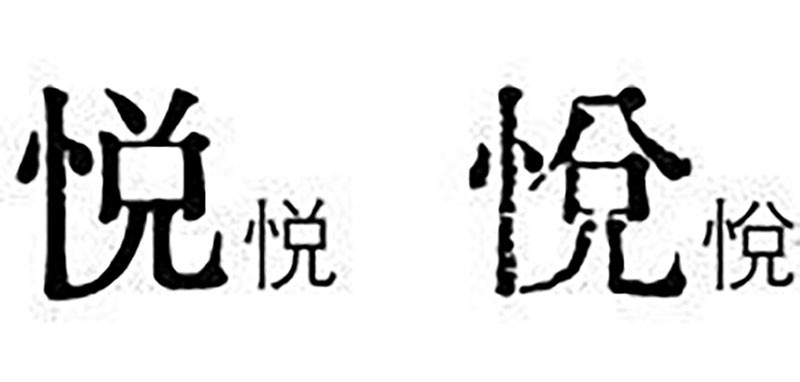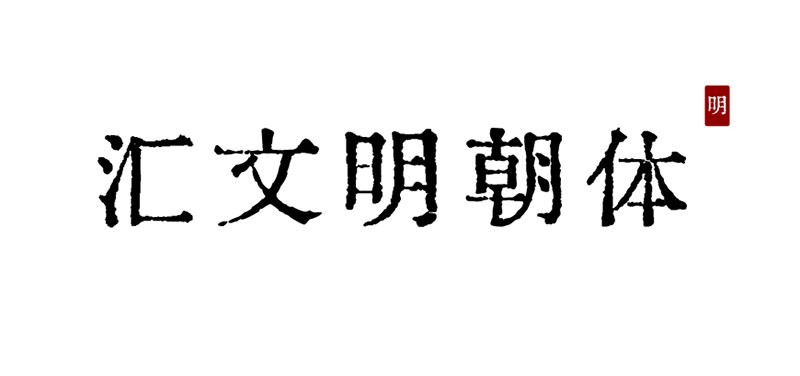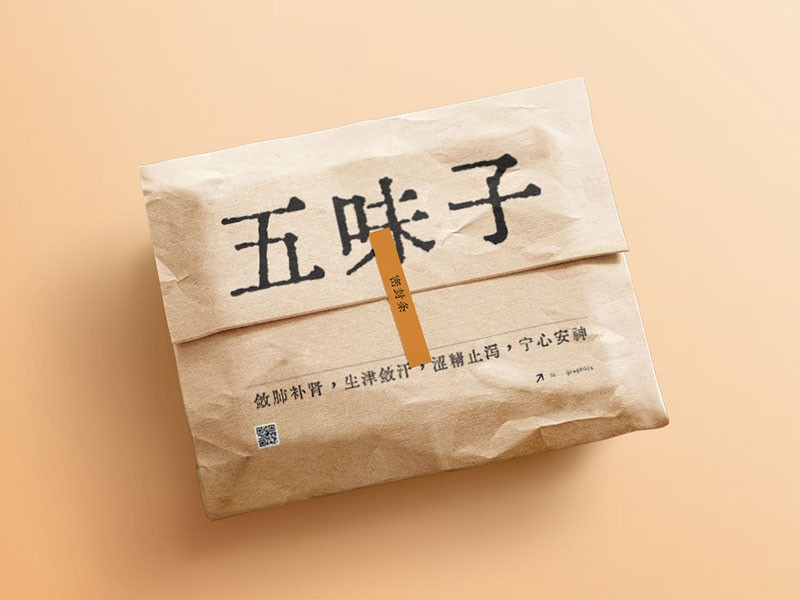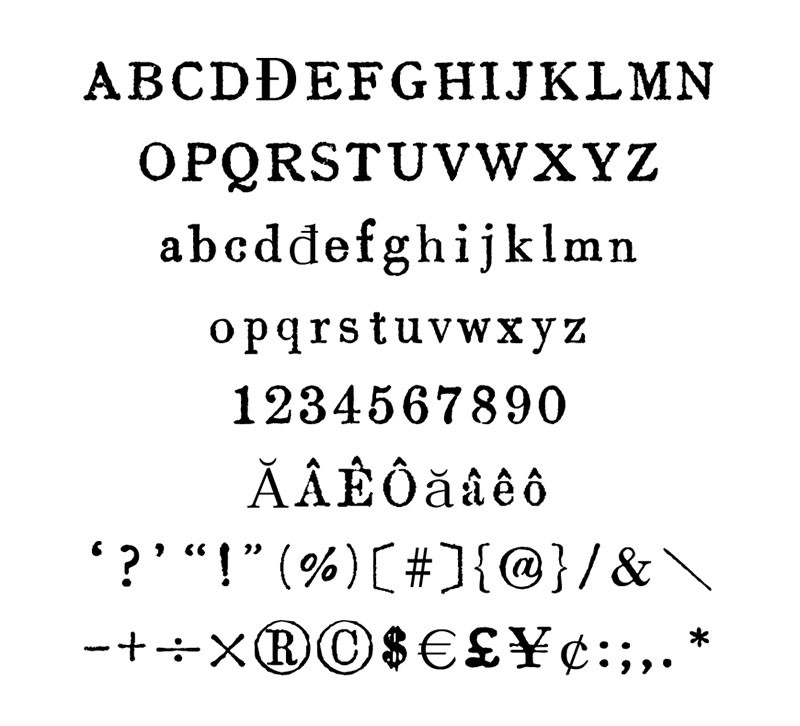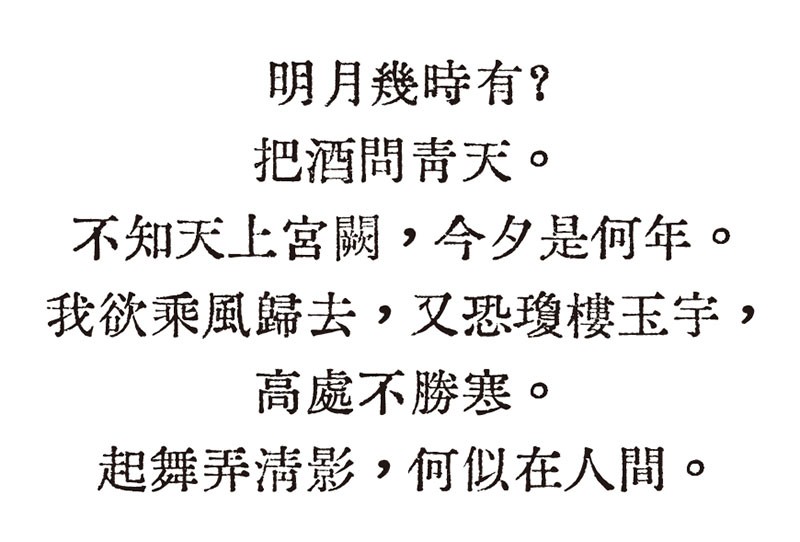
汇文明朝体创作于作者天王帝廷扫描《文汇报》上面的《汉字简化方案草案》。后来又收集、扫描了各种历史文献资料,汇总挑选而形成的一款字体。故名「汇文明朝体」。作者声明此字体可免费用于印刷、显示、嵌入电子文档设备等,可以使用此字体开发新字体,但禁止单独出售本款字体。
汇文明朝体的字形来源主体为五六十年代官方各种汉字改革文件。简体字部分基本复原汉字简化后、字形改造前的书籍印刷体样貌。繁体字、传承字部分基本还原民国至共和国初期字形样貌。是比较原滋原味的旧铅字印刷风格。
旧字形有单独编码,但是简体汉字标准 和 繁体汉字标准日常都使用新字形的:都从旧(但采用不同来源让字形有所区别)
简体汉字标准和繁体汉字标准使用不同编码的:保留新字形,各从其形。